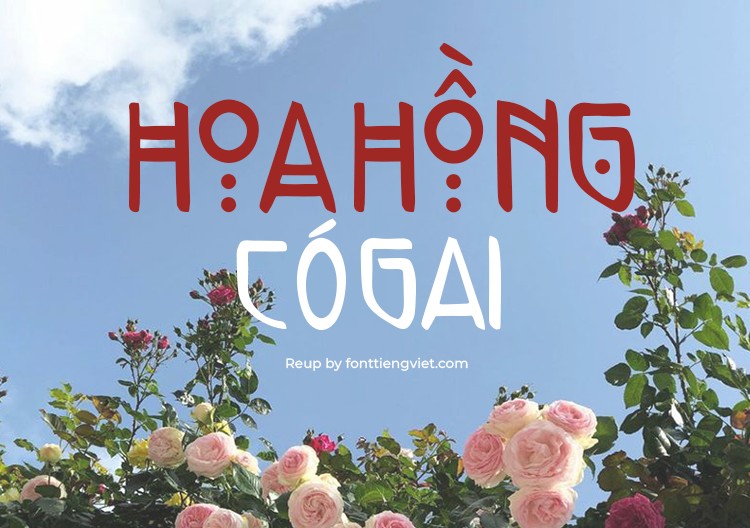
Font việt hóa MTD Elodie là một bộ phông chữ mang phong cách Art Nouveau đầy tinh tế, giúp các bạn học sinh và giáo viên dễ dàng tạo ra những tác phẩm trình bày ấn tượng. Trong thế giới đồ họa, việc lựa chọn một Font Miễn Phí nhưng vẫn đảm bảo tính thẩm mỹ cao luôn là ưu tiên hàng đầu. Elodie sở hữu những đường nét mảnh mai, uốn lượn mềm mại, rất phù hợp cho các chủ đề về nghệ thuật, lịch sử hoặc trang trí bìa báo tường. Phiên bản này đã được MTD Việt hóa hoàn chỉnh, loại bỏ lỗi hiển thị tiếng Việt giúp văn bản luôn mượt mà.
Đặc điểm nổi bật của Font việt hóa MTD Elodie
Phong cách cổ điển quyến rũ
Được lấy cảm hứng từ những năm đầu thế kỷ 20, bộ chữ này mang lại cảm giác hoài cổ nhưng vẫn rất hiện đại. Các ký tự được thiết kế với độ tương phản nhẹ nhàng, tạo nên vẻ ngoài thanh lịch và sang trọng cho mọi khung hình.
Tính ứng dụng cao trong học đường
Các em học sinh có thể sử dụng bộ chữ này để thiết kế thiệp chúc mừng, slide thuyết trình hay các tiêu đề tiểu luận sinh động. Nhờ cấu trúc rõ ràng, người xem dễ dàng tiếp nhận thông tin mà không bị rối mắt bởi các chi tiết rườm rà.
Cách sử dụng Font việt hóa MTD Elodie hiệu quả
Để phát huy tối đa vẻ đẹp của bộ chữ, bạn nên kết hợp nó với các tông màu pastel hoặc họa tiết cổ điển. Việc điều chỉnh khoảng cách dòng và kích thước chữ phù hợp sẽ giúp tổng thể thiết kế trở nên hài hòa và chuyên nghiệp hơn.
Kết luận về bộ font nghệ thuật